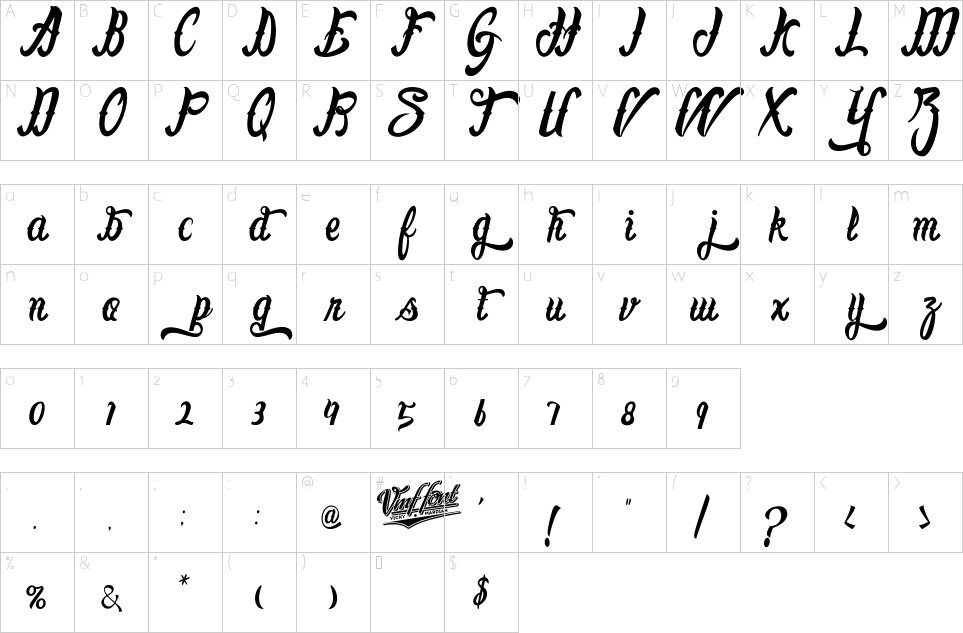
Lafayet Scripts Font – Download Grátis
A Lafayet Scripts é uma nova adição à família das fuentes gratuitas para Windows e Mac. Ela foi projetada por Vicky Mardian e já foi baixada mais de 60 mil vezes, mostrando sua popularidade crescente na comunidade de design gráfico. Com linhas elegantes e sutis nuances, a Lafayet Scripts oferece um ar sofisticado que se adapta perfeitamente para títulos, cabeçalhos e textos de apresentação. A sua facilidade de uso torna-a uma escolha popular entre designers e desenvolvedores que procuram fontes com uma aparência moderna e versátil sem precisar recorrer a fontes pagas. Com ela, você pode adicionar um toque único à sua design gráfico, enquanto beneficia-se dos benefícios de usar uma fonte gratuita.